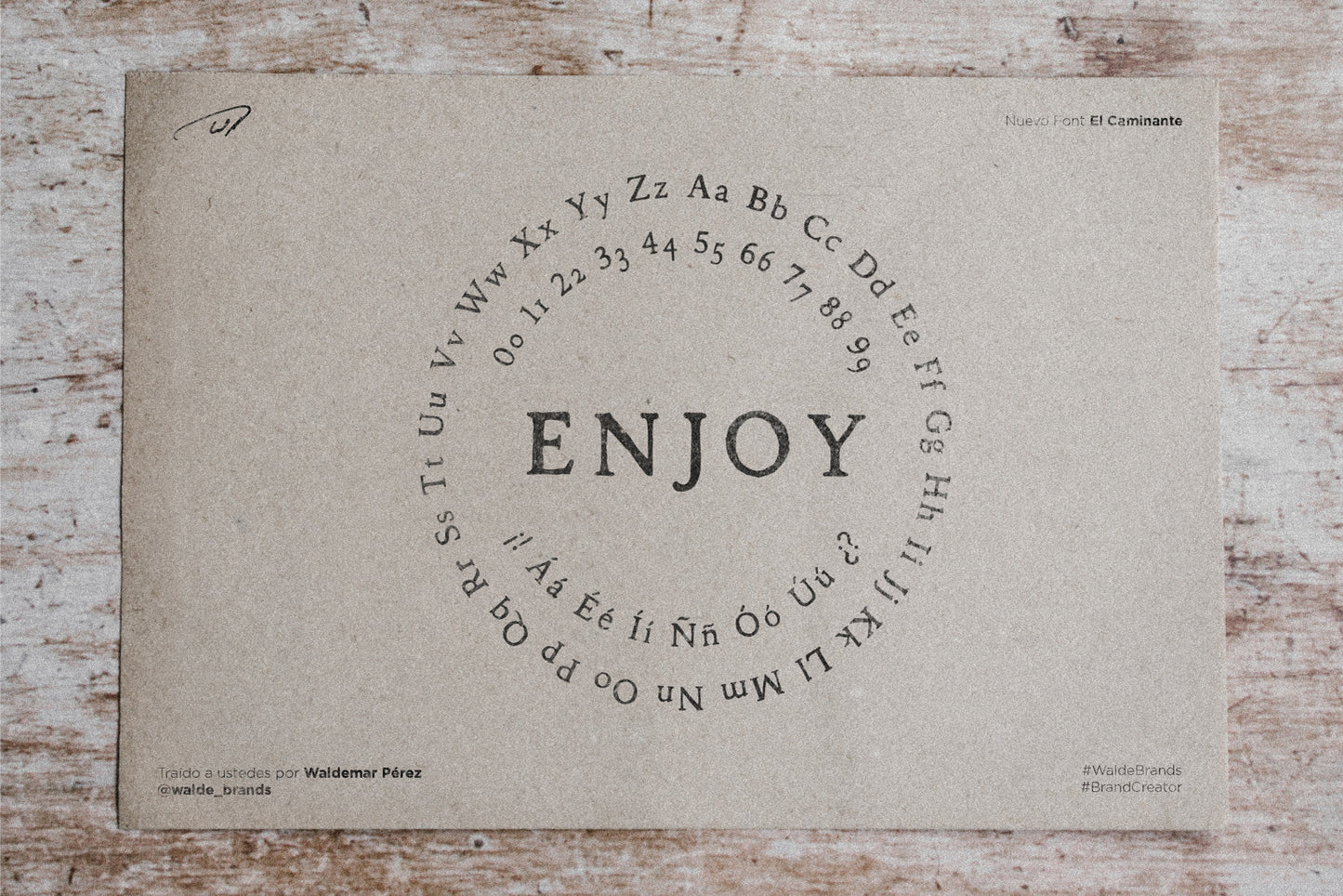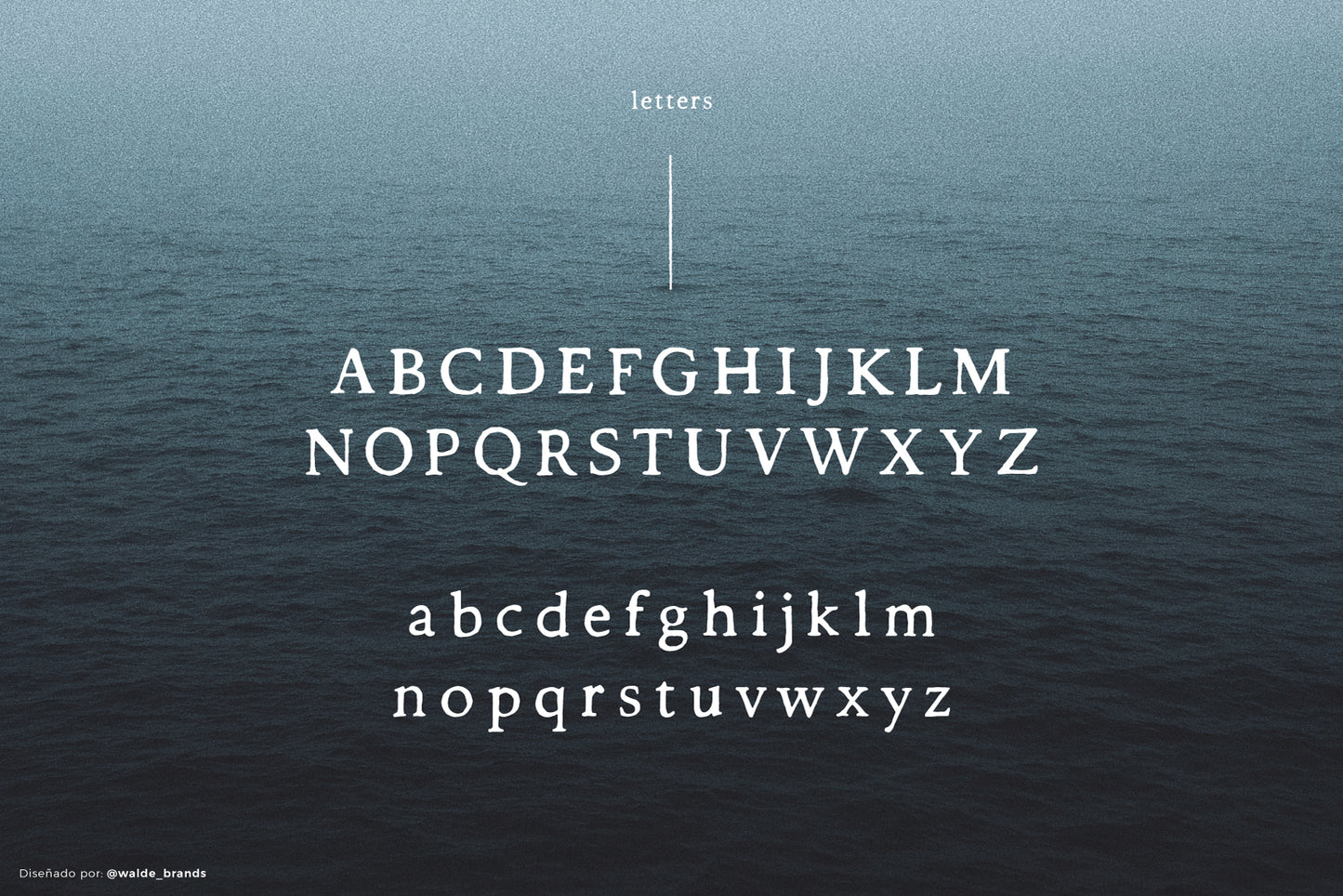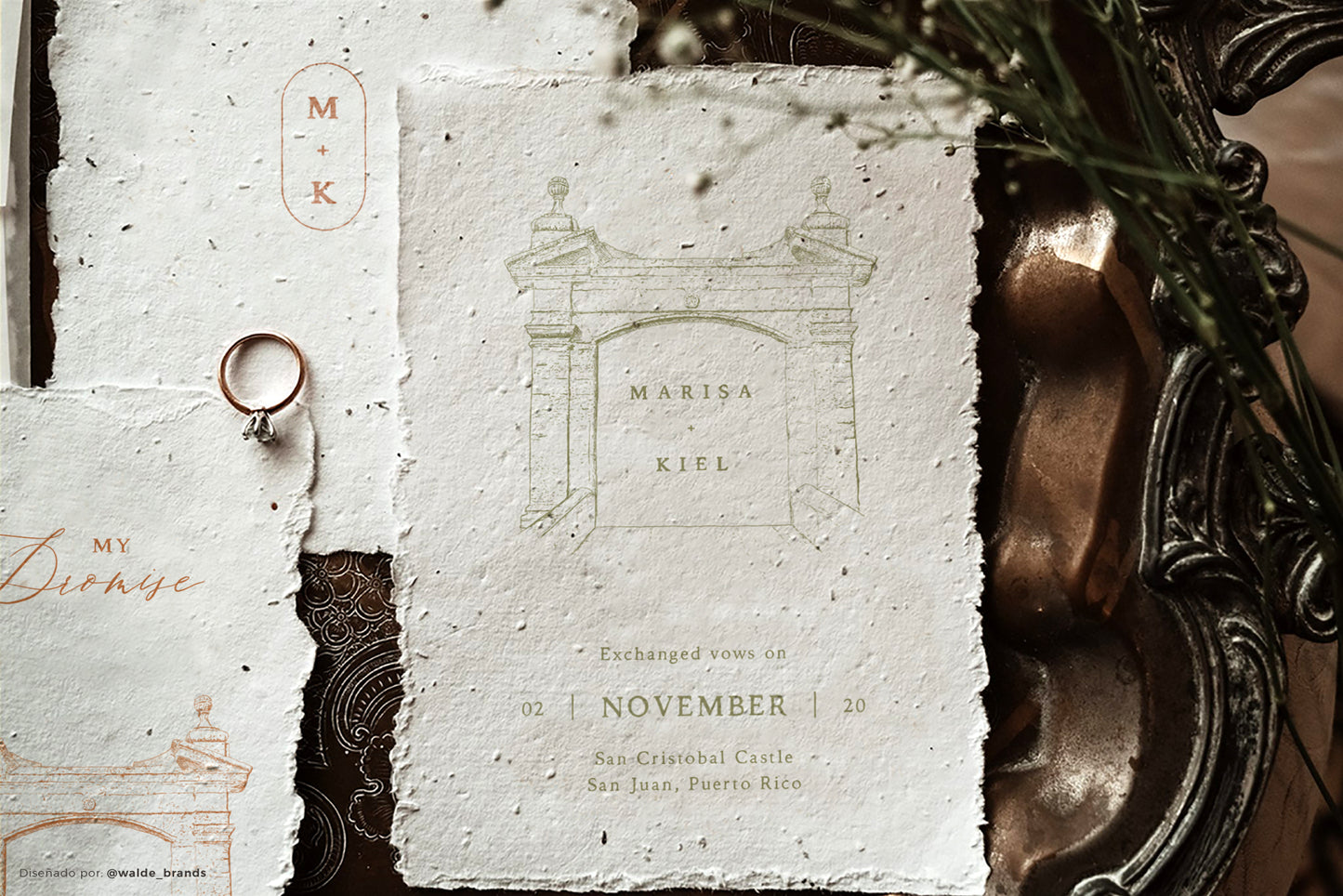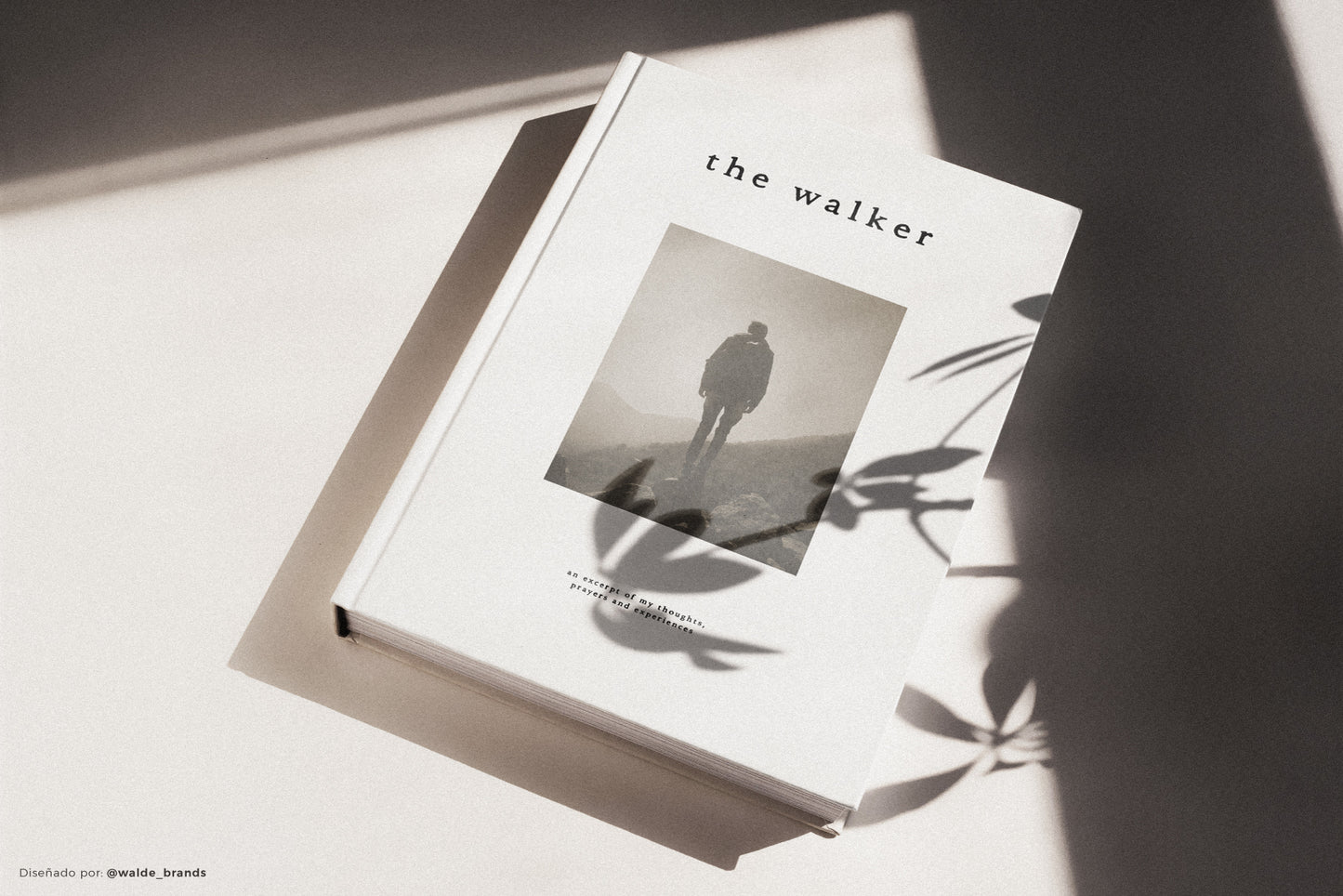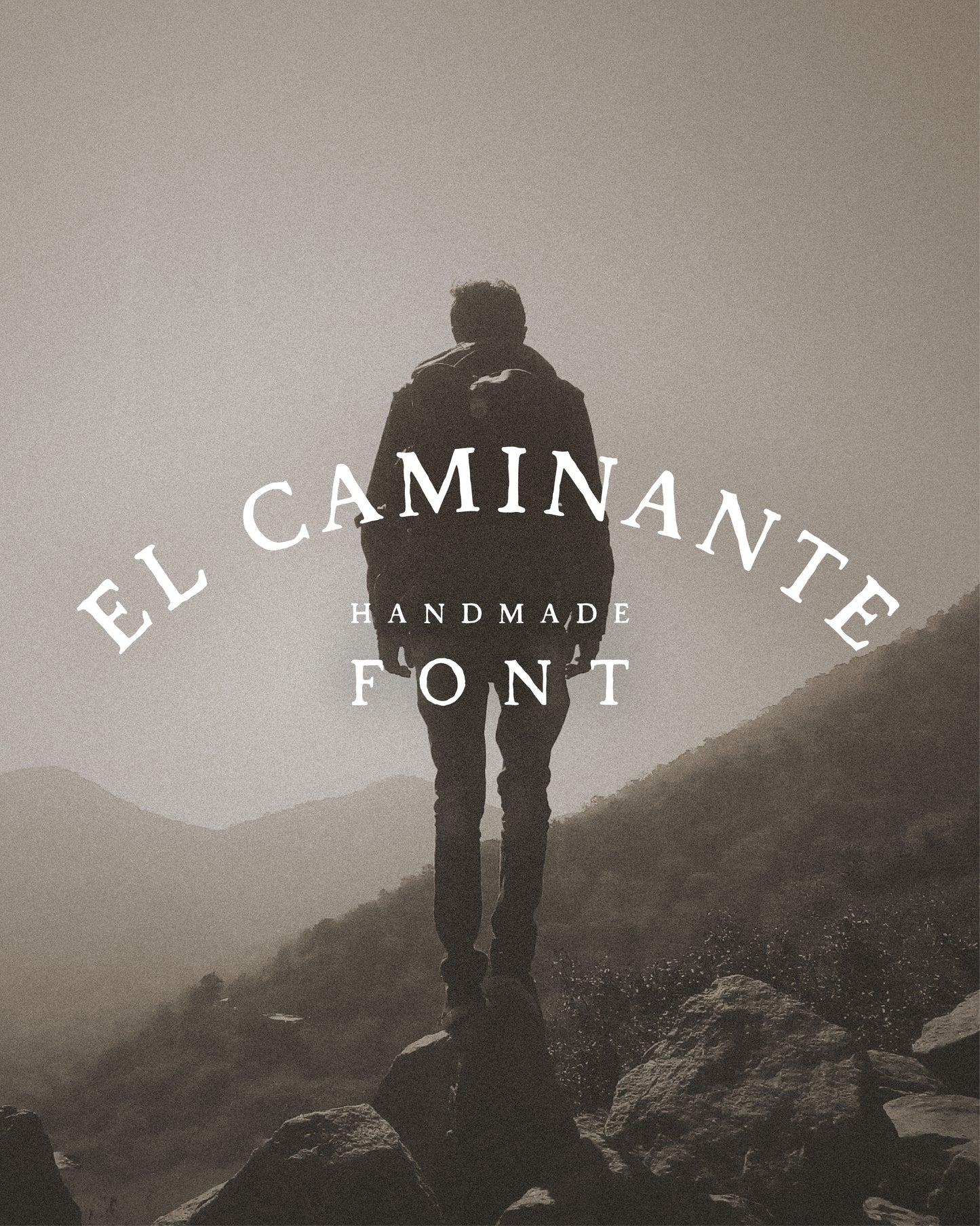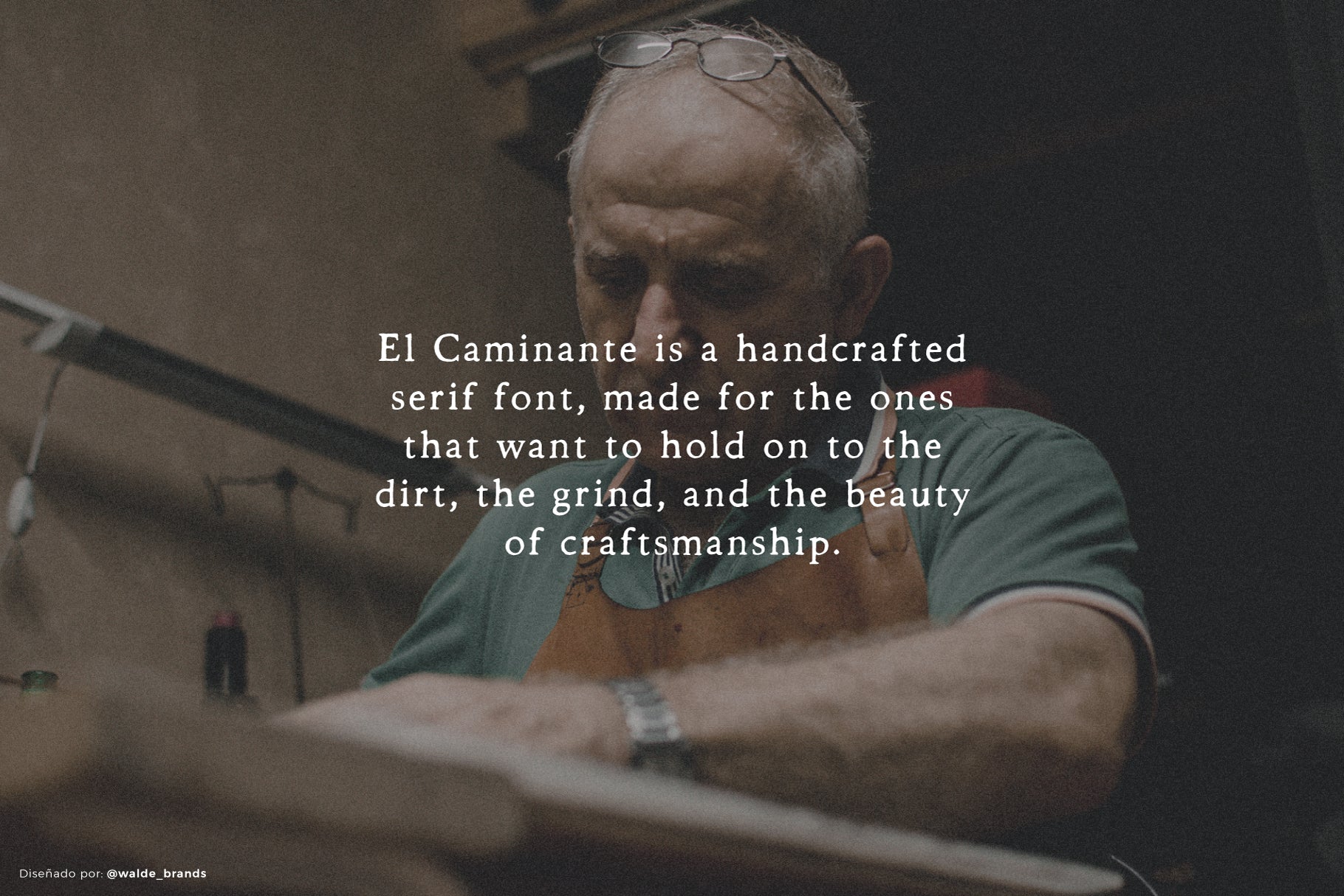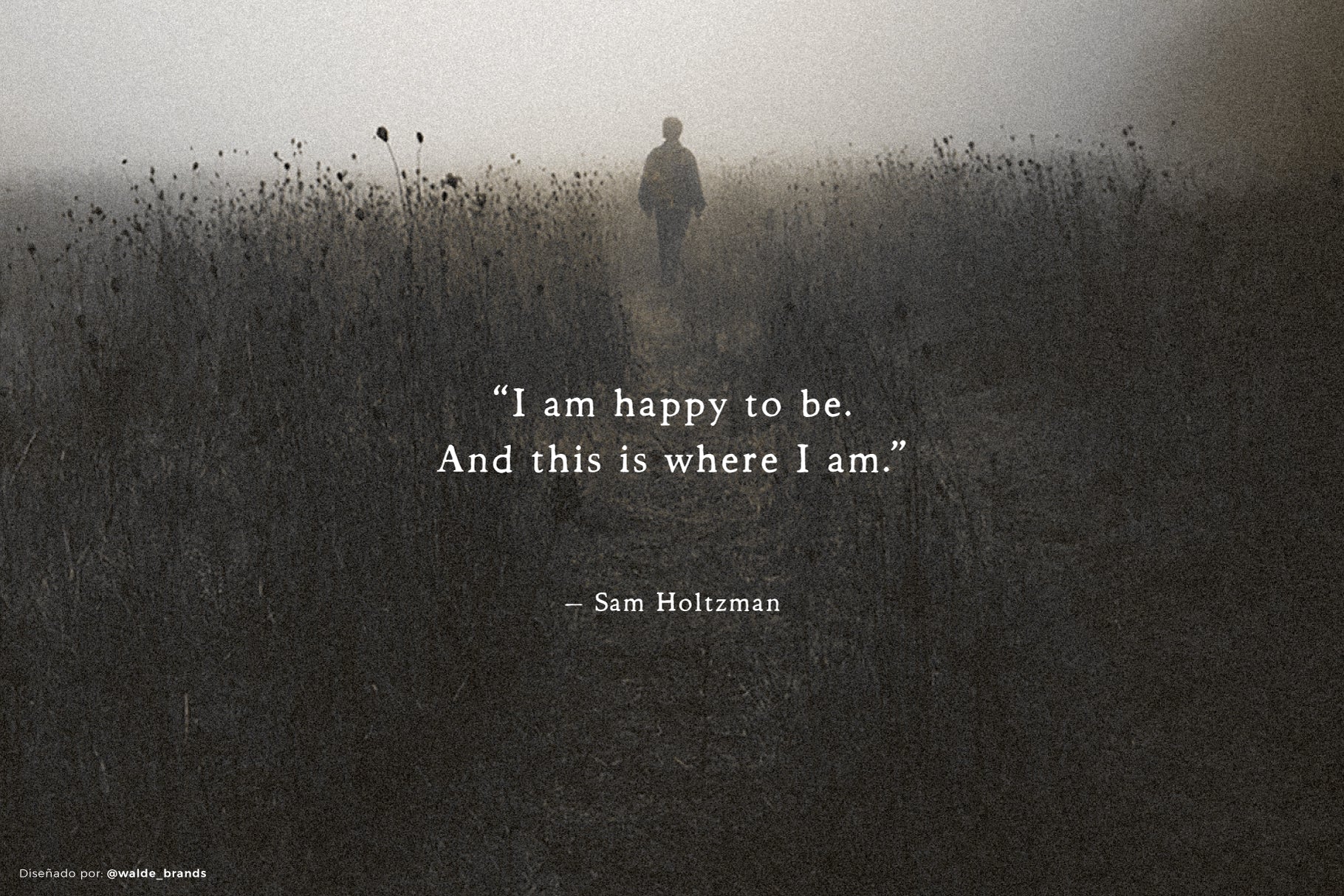
Una tipografía hecha a mano, robusta y elegante, con un estilo clásico y un hermoso contraste. Creada para quienes valoran la tierra, el esfuerzo y la belleza del trabajo artesanal. Perfecta para diseñar piezas elegantes y personalizadas como logotipos, títulos, portadas de libros y más. La fuente incluye soporte multilingüe (cada letra y símbolo fue dibujado a mano individualmente) y también ofrece números alternativos.